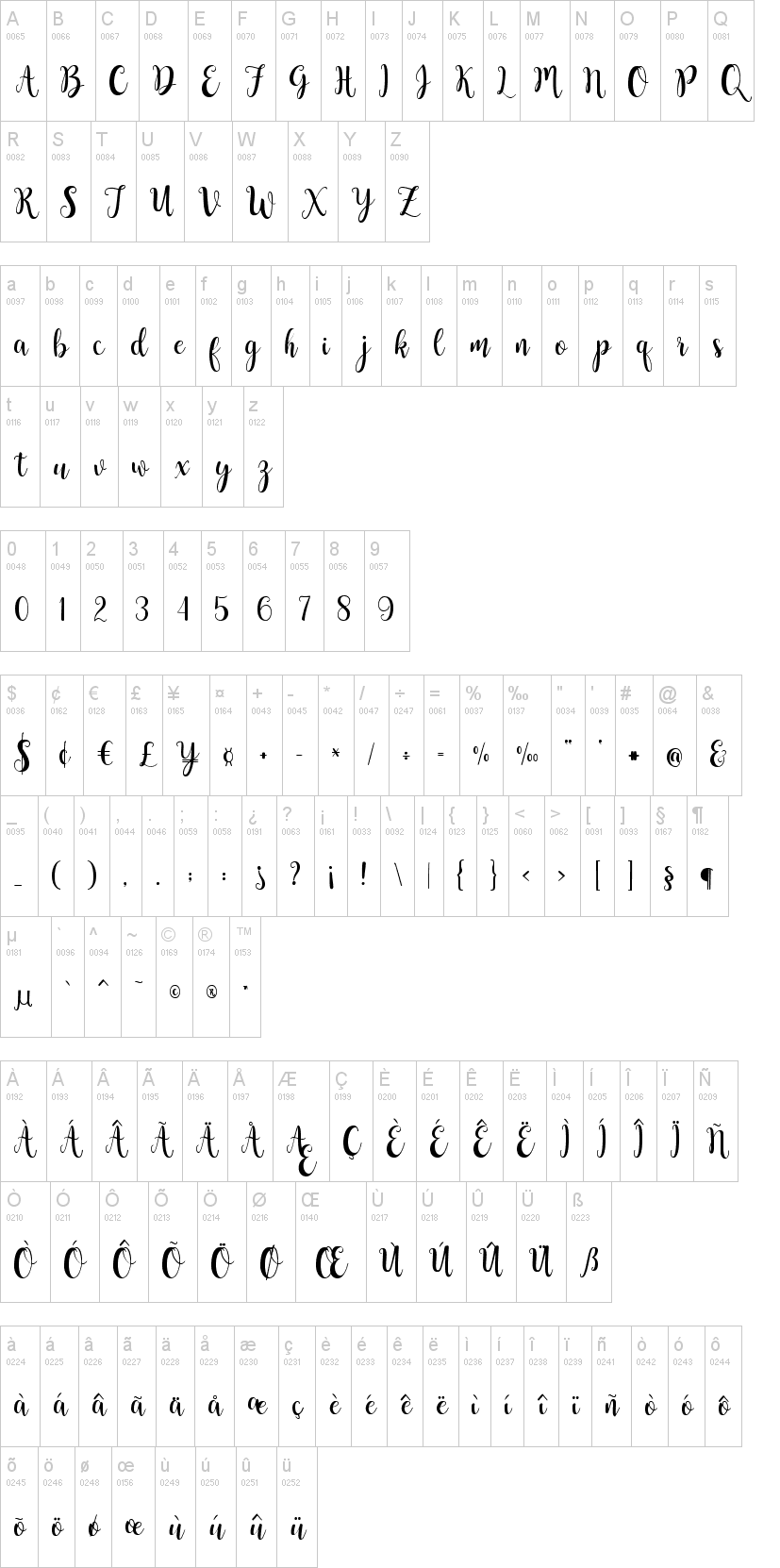
? Buttercup 是一款英式古典风格的字体,由英国设计师Andy Mangold设计。它具有浓郁的英式古典风格,带有非常柔和的轮廓,是一款非常优雅的字体。Buttercup字体有着优雅、精致、细腻的外观,可以用于各种类型的文本,特别适合用于商业、报纸和杂志等文本类型的设计。内容介绍
Buttercup是一款非常不错的手写艺术字体,具有很好的视觉感,适合于文化类的宣传设计、商业类品牌的广告和产品包装设计以及个性化文字排版等较多场景。